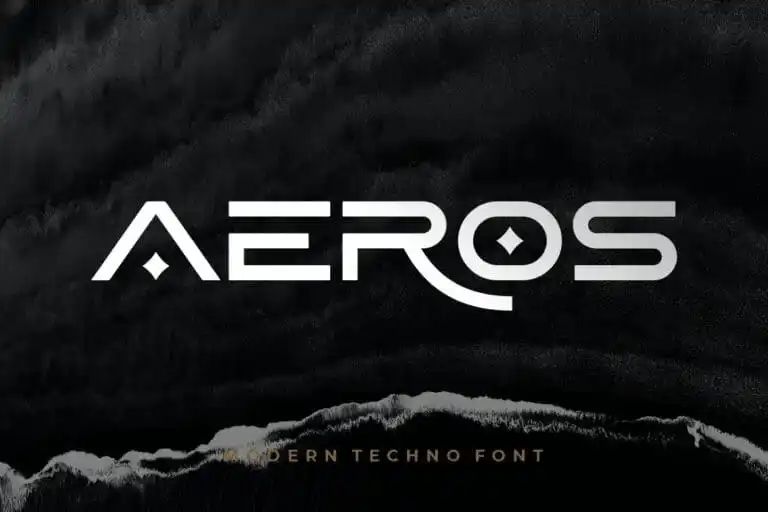
Aeros Display Font é uma seleção ideal para qualquer projeto que exige modernidade e simplicidade no design tipográfico. Desenvolvida pelo designer HansCo, esta fonte mono é perfeita para seletor de logotipo, identidades corporativas, embalagens, materiais publicitários, roupas personalizadas, convites e até mesmo capas de livros. Com os detalhes básicos da letras maiúsculas, minúsculas, números e sinais de pontuação disponíveis, a Aeros Display Font oferece suporte para múltiplas línguas. Esta fonte não apenas se adapta perfeitamente às aplicações digitais modernas, como também ao design físico das publicações impressas. Sujeite-se à simplicidade e elegância de Aero Display, uma escolha versátil que atende a um amplo espectro de necessidades de design gráfico.